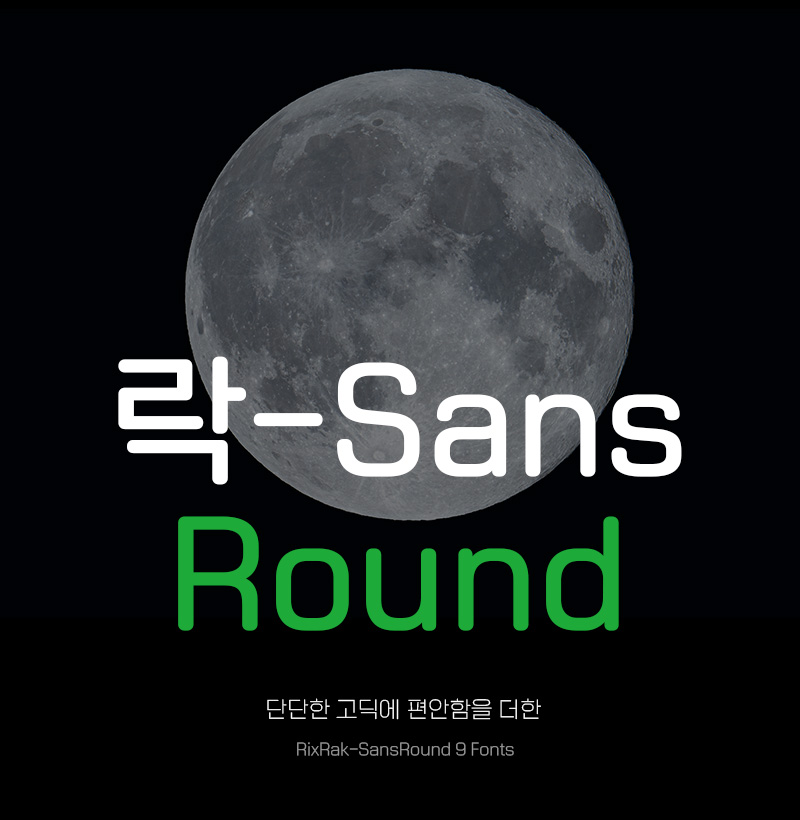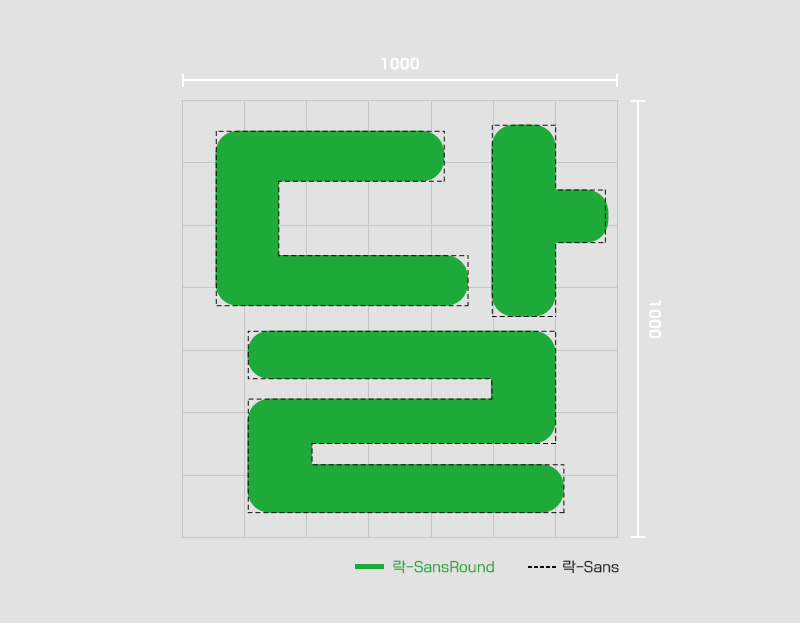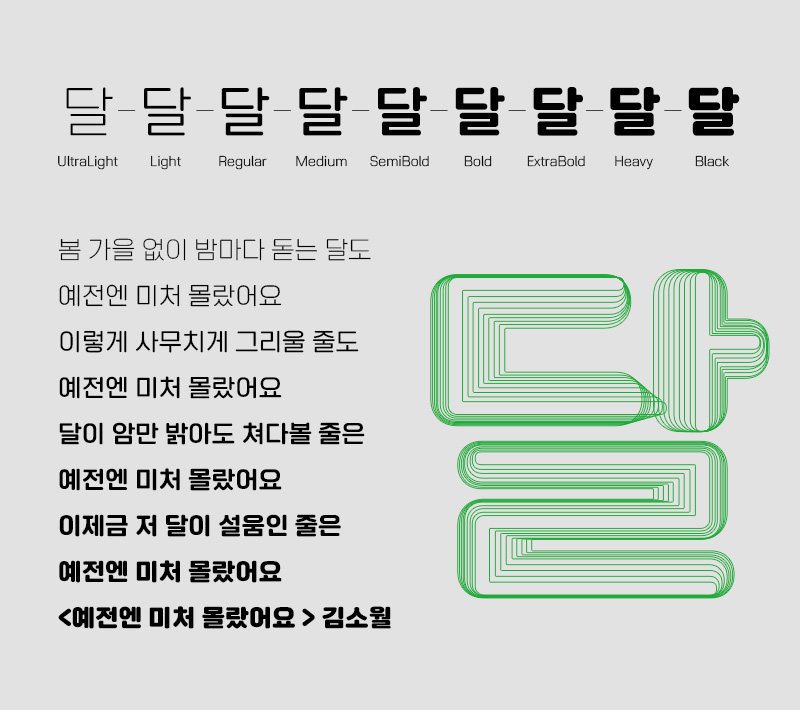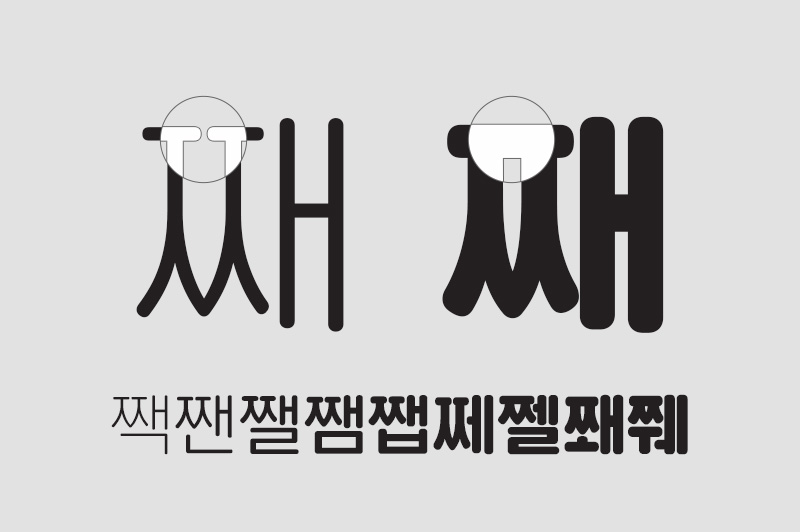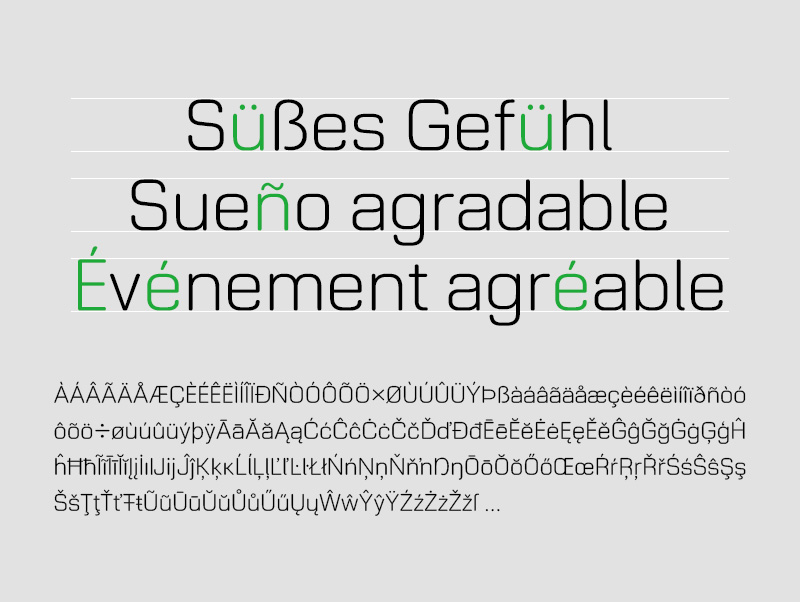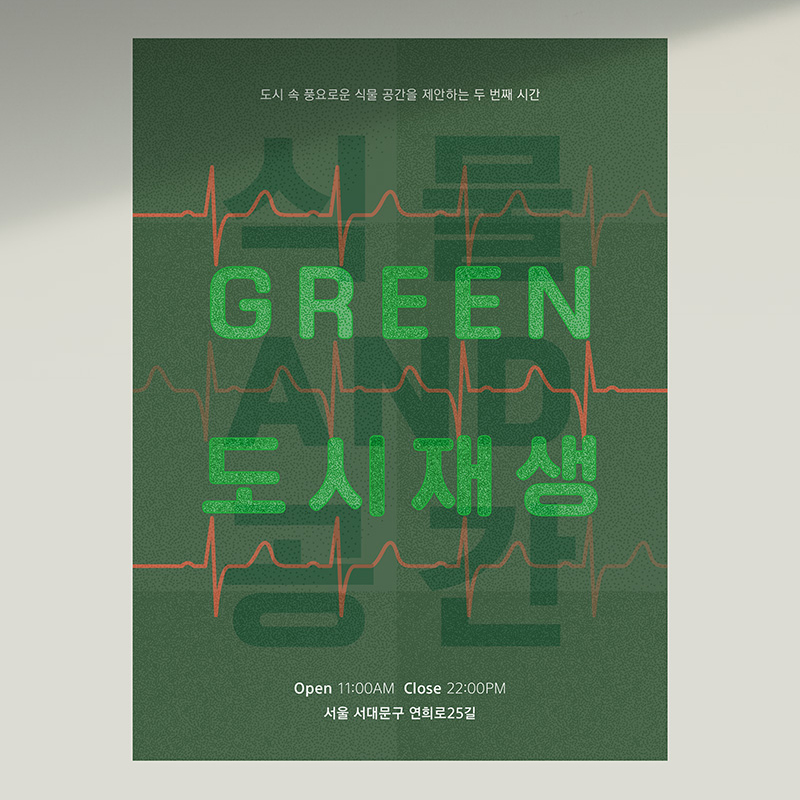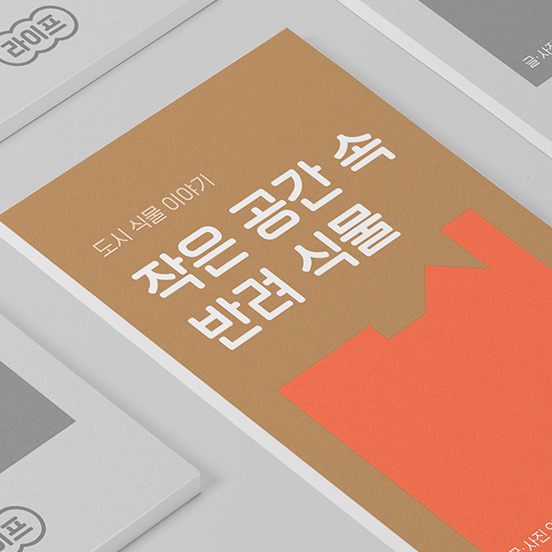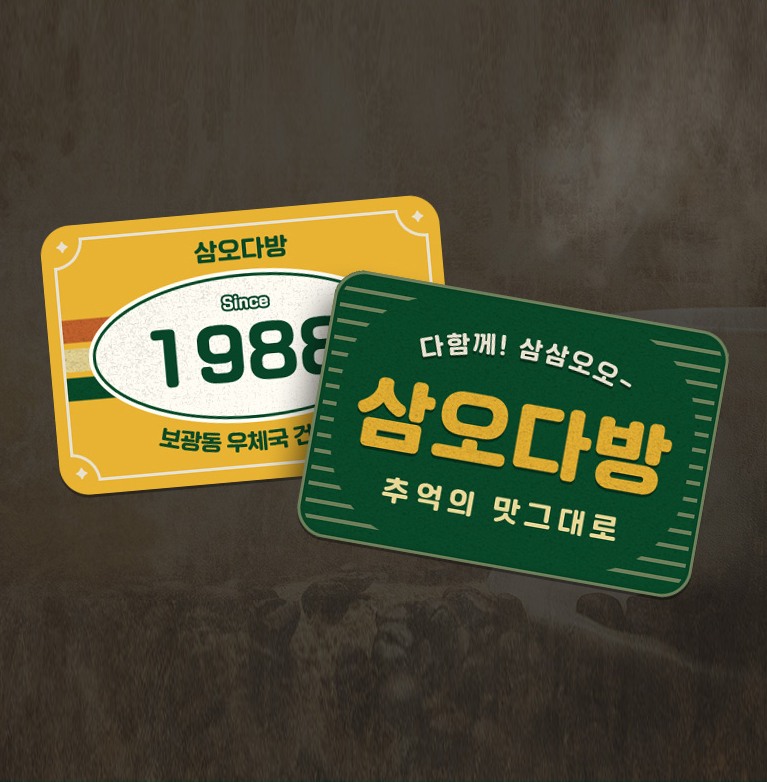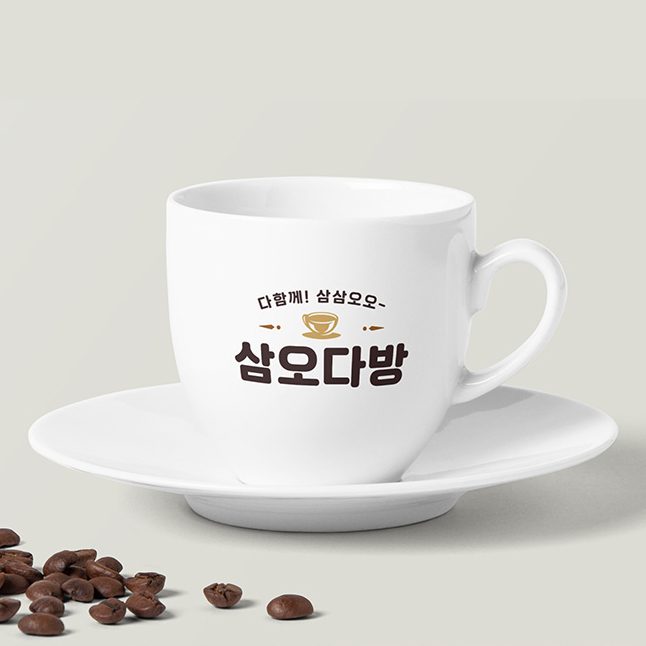
안녕하세요! 11월에 벌써 두 번째 신서체로 인사드리게 되었습니다.(열일하는 우리 디자이너님들(ง •̀_•́)ง) 이번 신서체는 기존 Rix락-시리즈의 락-산스 폰트에서 파생된 서체로 깔끔하고 담백한 고딕 Rix락-Sans에 부드러운 굴림을 더한 특별한 폰트입니다. 꽉 찬 네모틀의 단단한 골격에 유연함을 더해 편안함과 가독성을 높여 새로운 서체로 탄생했답니다.
Designer Says 어떻게 기획하게 되었나. Rix락-Sans(이하 락산스)는 남성적 중립성이 있습니다. 반면 Rix락-Serif(이하 락세리프)는 여성적 중립성이 있다고 할 수 있죠. 락산스는 남성적인 골격과 요소로 인해 자칫 차가운 느낌을 받을 수 있습니다. 그렇기 때문에 여성스러운 굴림의 요소를 넣어 락산스에 부드러운 느낌을 주고자 하였습니다. 차갑고 모던한 이미지와 따뜻하고 편안한 요소가 만나 이중적인 새로운 매력을 가질 수 있도록 제작하였습니다. 락산스, 락세리프, 락산스굴림이 모여 하나의 패밀리 군으로 형성되어 사용자에게 더욱 다양한 곳에 사용되도록 기획하였습니다.
단단한 고딕에 편안함을 더하다
단단하고 모던한 고딕도 편안함을 줄 수 있다면 어떨까요? 부드러운 굴림을 가진 Rix락-산스굴림은 기존 고딕인 락-산스의 깔끔하고 딱 떨어지는 세련된 느낌에 편안함을 더했습니다. 왠지 정리벽이 있을 것 같은 반듯한 친구 락산스에 유연함 한 스푼을 더한 느낌이랄까요˘◡˘
락-산스와 비교! 기존의 단단한 골격이나 굵기는 유지하되 라운드를 추가한 모습입니다. 산스와 동일하게 굵기는 총 9종으로 세밀하게 작업해 다양한 활용도가 예상되는데요. 굵기가 다양하고 기본 서체인만큼 디테일 하나하나 신경쓸 부분이 많은데 여러 디자이너들이 제작에 함께해 최소한의 시간에 최대한의 퀄리티를 만들어냈다는 후문도,, 정말이지 우리 디자이너님들 채고.
가장 얇은 UltraLight부터 가장 두꺼운 Black까지 세부화된 웨이트에 따라 적당한 굴림과 공간 구성을 고민했습니다.
획이 많은 ㅐㅒㅔㅖㅙ ㅞ 중성과 만나는 ㅉ꼴 디자인의 경우, 두꺼운 굵기에서 가운데 공간을 붙여 가독성을 보완하였습니다. 편안하게 읽히도록 디테일한 부분을 더욱 신경 써서 제작했습니다.
영문도 국문의 특징에 적합한 형태로 글줄과 가독성을 고려하여 제작되었으며, 라틴 확장(Latin-1 / Latin Extended-A)을 지원하여 다양한 언어권을 포용합니다.
포스터, 브로슈어, 로고, 패키지 등 다양한 디자인에 활용하기 좋은 Rix락-산스굴림. 서체 자체가 깔끔, 담백해서 어디에나 잘 어울립니다. 눈에 잘 들어오는 두꺼운 굵기는 제목용으로 활용하기 좋고, 중간, 얇은 굵기로는 짧은 문구나 설명글에 활용하기에 좋습니다. 넓은 스펙트럼의 웨이트로 모던함, 편안함, 가독성까지 놓치지 마세요 '◡'